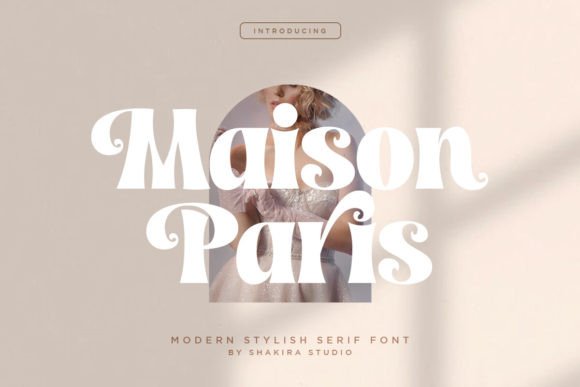
Maison Paris
หากคุณกำลังมองหาเนื้อหาคุณภาพสูงเช่น Maison Paris แพ็คเกจพรีเมียมนี้เป็นตัวเลือกที่ยอดเยี่ยมสำหรับโปรเจ็กต์สร้างสรรค์ของคุณ
ไม่ว่าคุณจะสร้างผลิตภัณฑ์ POD (Print on Demand) คำเชิญงานแต่งงาน หรือกราฟิกโซเชียลมีเดีย Maison Paris ก็เหมาะสมอย่างยิ่ง